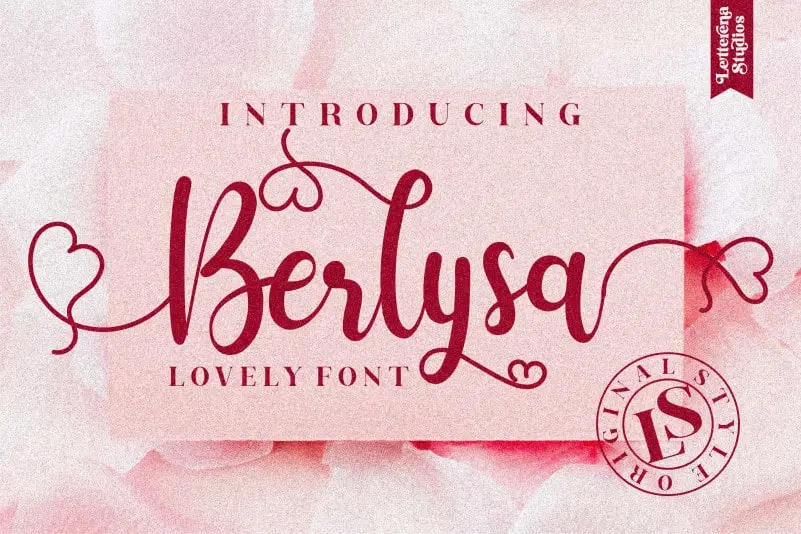
Berlysa Script é uma fonte script romântica e bela que adicionará um toque pessoal a qualquer projeto visual. Esta fonte versátil atinge desde cartões de cumprimento até headlines, oferecendo uma variedade incrível de aplicação. Ela também inclui todos os guilos e swashes em formato PUA, permitindo que você acceda facilmente a todos eles. É ideal para designers que buscam dar um toque especial a seus projetos, seja ele o próximo cartão de aniversário ou uma publicidade poderosa. Com Berlysa Script, cada projeto ganha vida através do seu personalismo único e delicado.